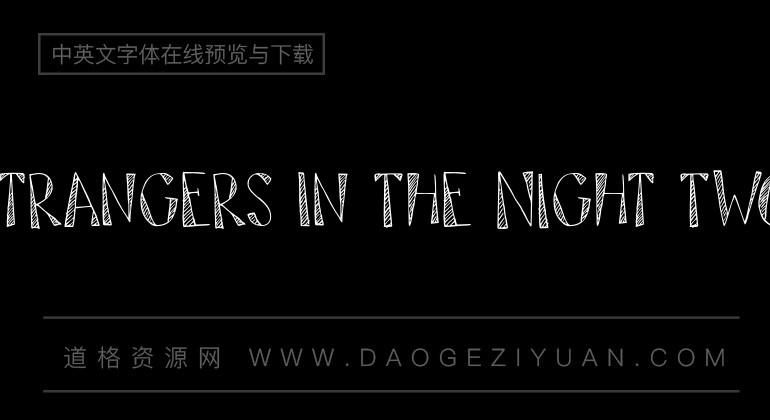
Strangers In The Night Two
Strangers In The Night Two 是一款由 Fontfabric 公司创作的字体。它是一款比较特别的字体,具有浪漫、优雅的风格,适合用于浪漫的标题、报道、封面等。字体包含多种字体风格,如细体、粗体、斜体等,可以满足不同的设计需求。它也支持多种语言,可以用于欧洲、亚洲等地区。
Strangers In The Night Two是一款非常不错的手写艺术字体,具有很好的视觉感,适合于文化类的宣传设计、商业类品牌的广告和产品包装设计以及个性化文字排版等较多场景。